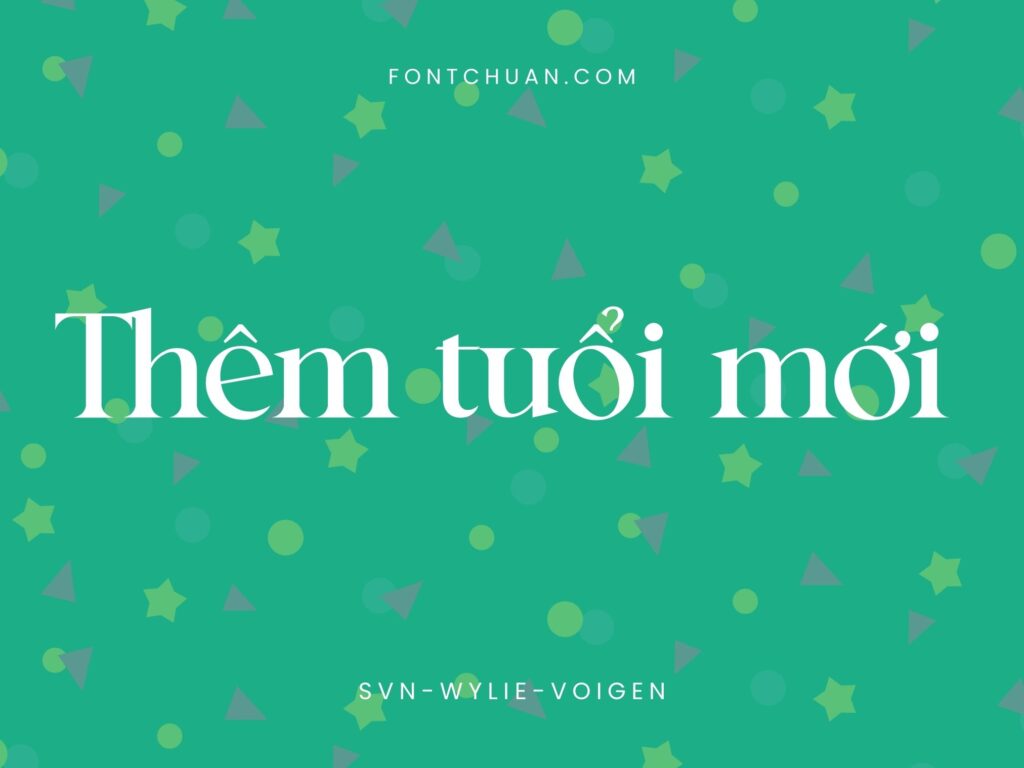
Font SVN Wylie Voigen Việt Hóa
Tác giả Font: Graphue
Font SVN Wylie Voigen là phiên bản Việt hóa của kiểu chữ Wylie Voigen, được thực hiện bởi Styleno.1 Fonts. Wylie Voigen là một Font Serif hiện đại, kết hợp giữa văn hóa và phong cách, mang đến sự độc đáo và thu hút trong thiết kế. Font này bao gồm các chữ cái in hoa, in thường, chữ số và ký tự đặc biệt, hỗ trợ đa ngôn ngữ, phù hợp cho nhiều mục đích sử dụng khác nhau như thiết kế logo, tiêu đề, bao bì sản phẩm và các ấn phẩm quảng cáo.
SVN Wylie Voigen lý tưởng cho các dự án thiết kế yêu cầu sự sang trọng và chuyên nghiệp, như thiết kế logo, tiêu đề, bao bì sản phẩm và các ấn phẩm quảng cáo. Các ngành nghề như quảng cáo, thiệp cưới và bất động sản có thể tận dụng font này để tạo điểm nhấn trong thiết kế. Ngoài ra, font cũng thích hợp cho các sự kiện như Tết, Giáng sinh, Valentine và các lễ hội khác.